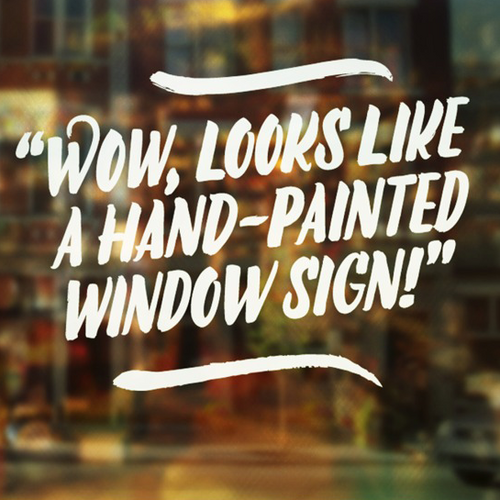
Die Jazz script von Emil Karl Bertell ist eine recht umfangreich ausgebaute Schreibschrift im amerikanischen Lettering-Stil. Die verbundene Grundschrift ist in zwei Strichstärken mit über 770 Glyphen verfügbar. Hinzu kommen zwei Zusatzfonts mit einem Versal-Alphabet sowie Schwungelementen. Dieser Satz aus vier Fonts ist zusätzlich in drei weiteren Ausführungen erhältlich: einer lichten Version sowie zwei Texturvarianten. Wie für OpenType-Schriften in diesem Stil üblich verfügen auch die Schnitte der Jazz Script über zahlreiche Ligaturen, Schwungbuchstaben und kontextbedingte Glyphen. Auch Titelschriftvarianten sind verfübar.